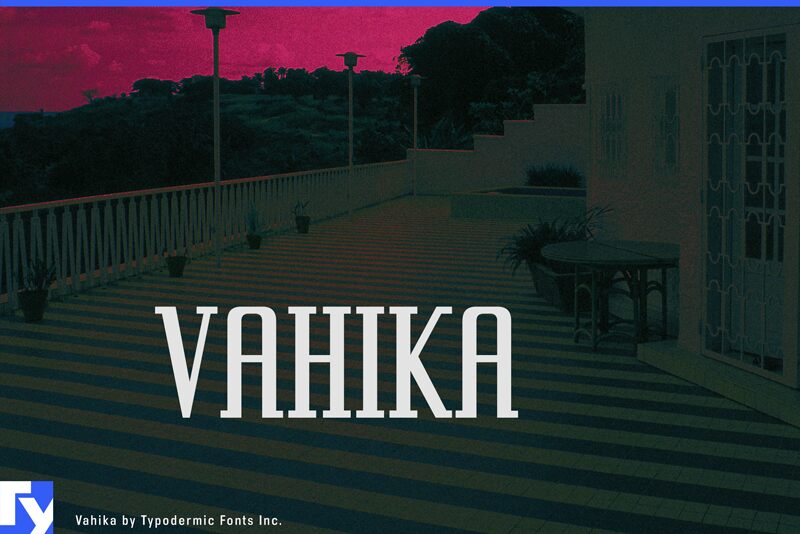
Vahika, creata da Ray Larabie di Typodermic Fonts Inc., presenta una miscela distintiva di eleganza ed efficienza nel campo dei caratteri slab serif. Il suo peso semi-light e la larghezza extra condensata creano un profilo sofisticato che parla sia di modernità che di tradizione. Le linee pulite e la struttura geometrica del carattere offrono un tocco contemporaneo alla robustezza classica degli slab serif, rendendolo una scelta eccellente per il design editoriale, il branding e le piattaforme digitali che cercano una fusione di chiarezza e personalità.
Le proporzioni strette del carattere Vahika lo rendono estremamente versatile per i layout in cui lo spazio è limitato, senza sacrificare la leggibilità. Che venga utilizzato per titoli che richiedono attenzione o per il testo principale che necessita di sottigliezza, il suo stile unico garantisce un'elevata visibilità con un'aria di raffinatezza. Il fascino estetico del carattere risiede nel suo equilibrio tra funzionalità e stile, posizionandolo come una risorsa per i designer che mirano a infondere nei loro progetti sia precisione che personalità.